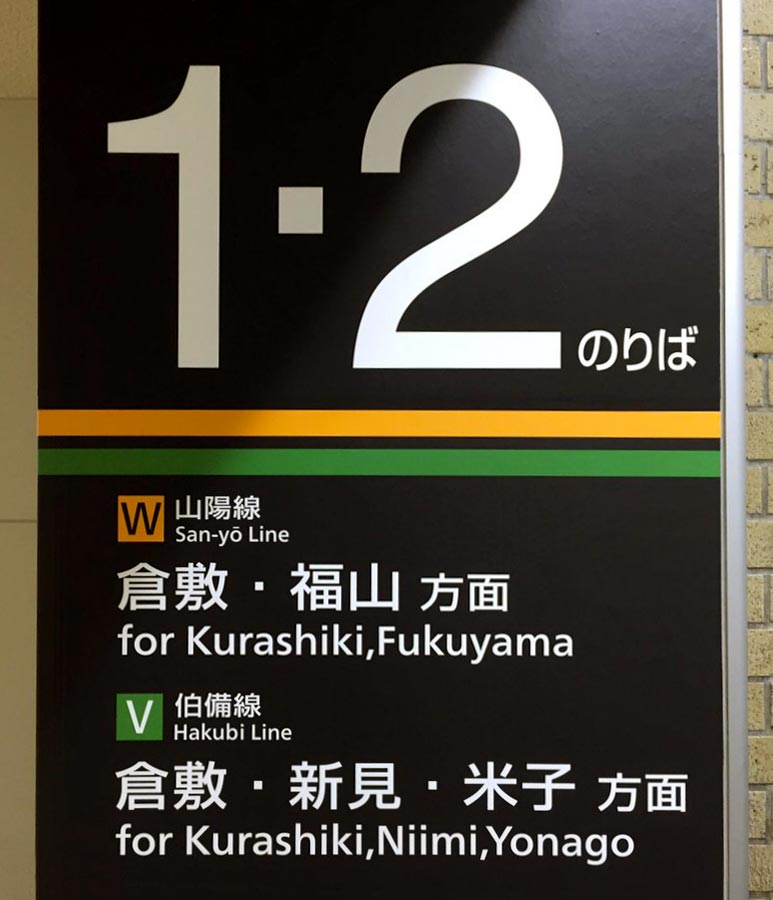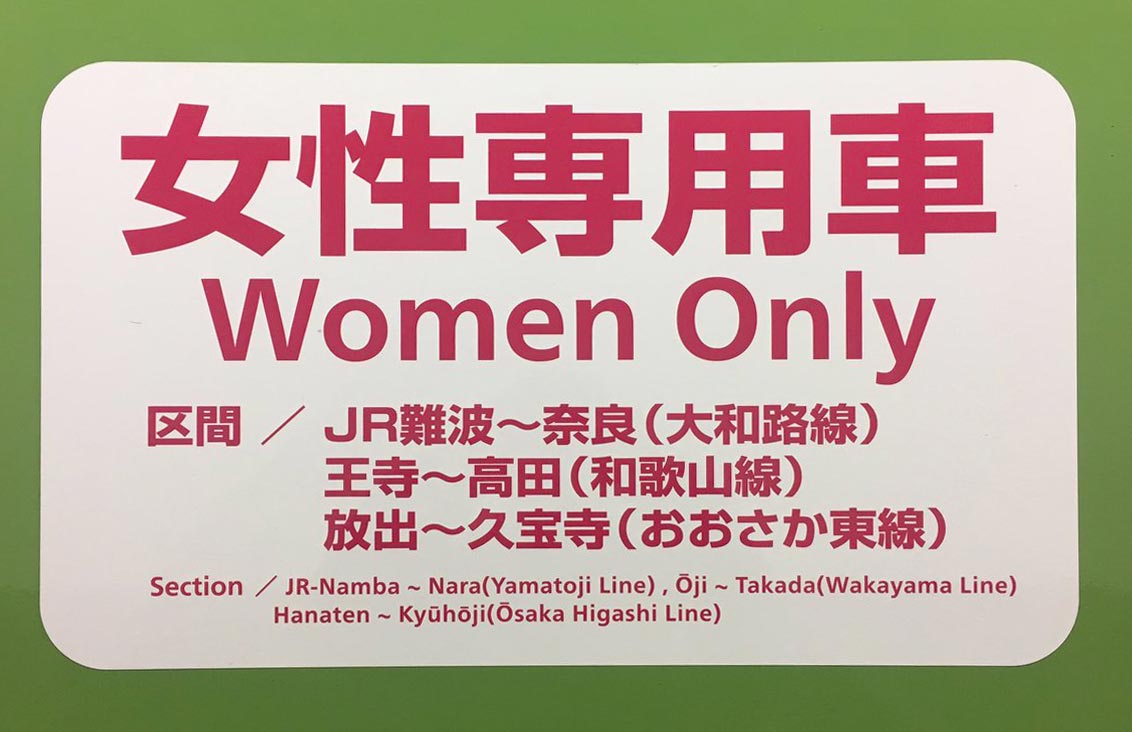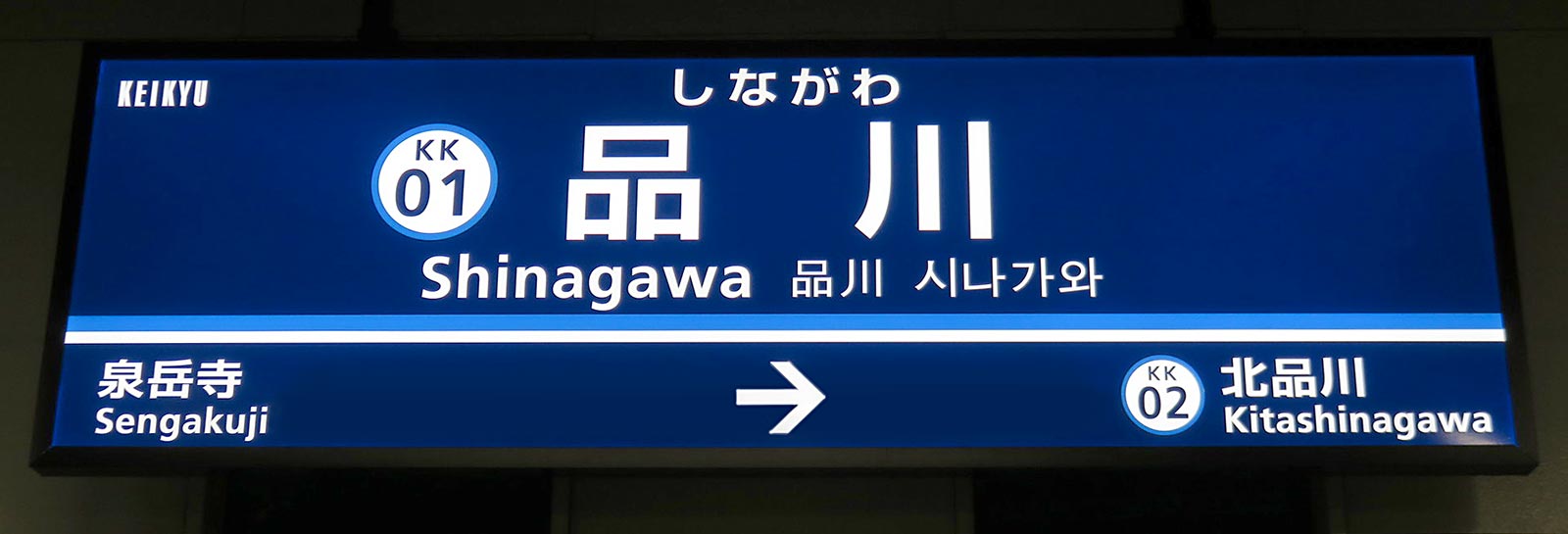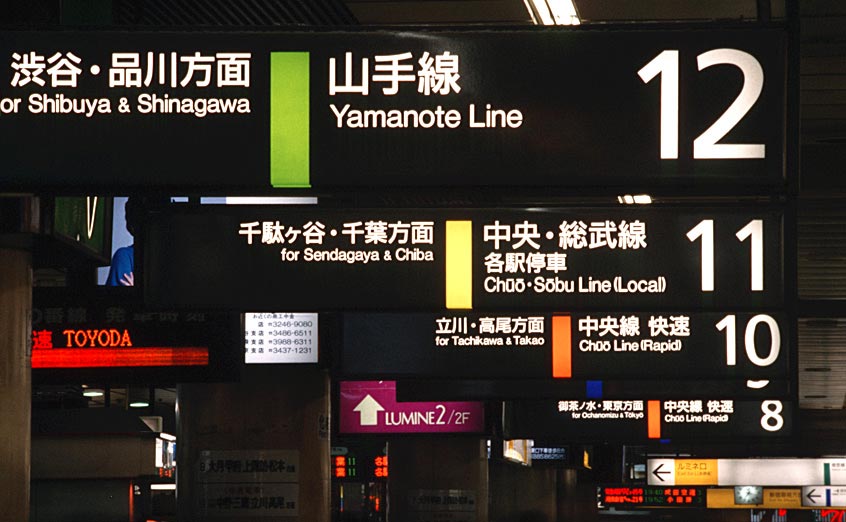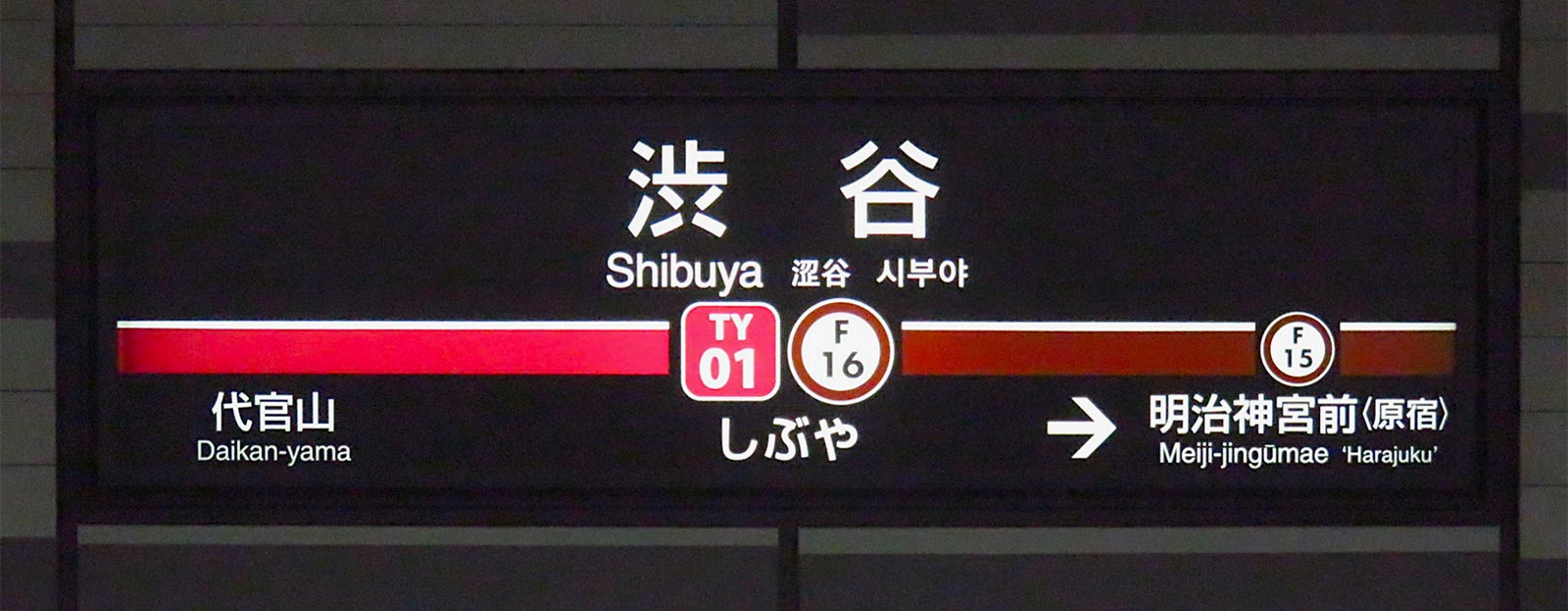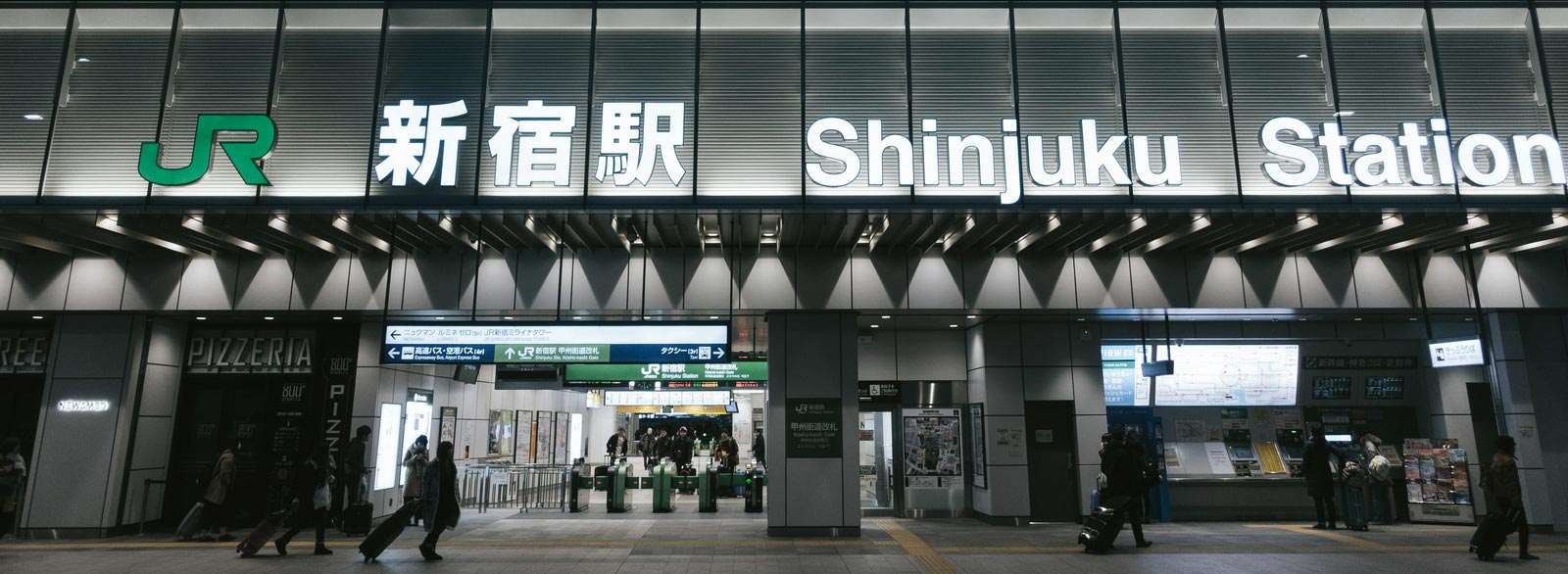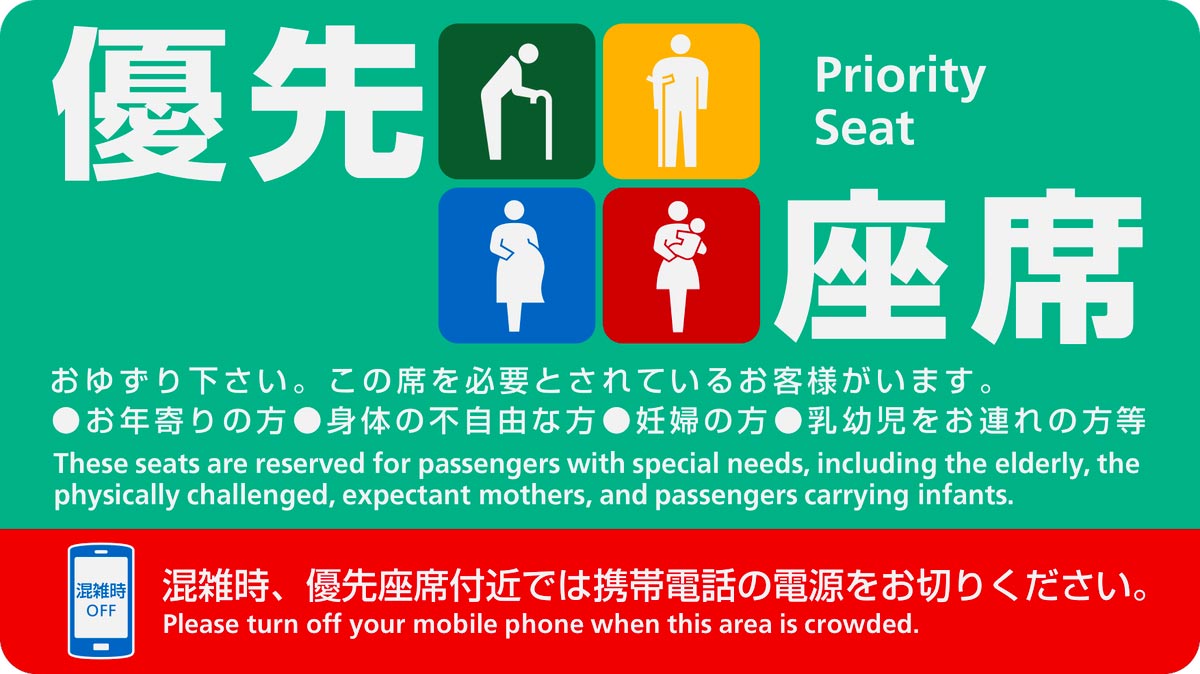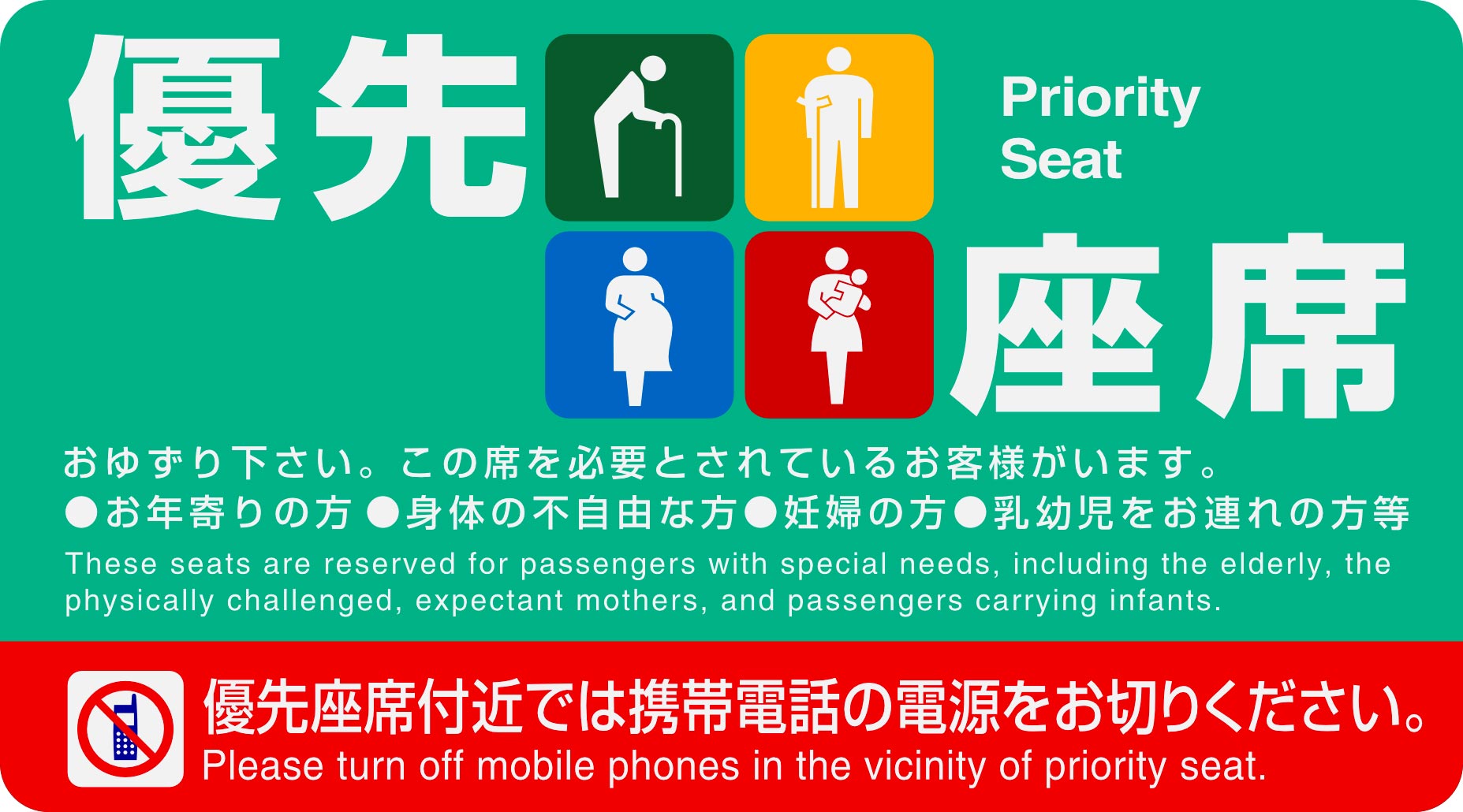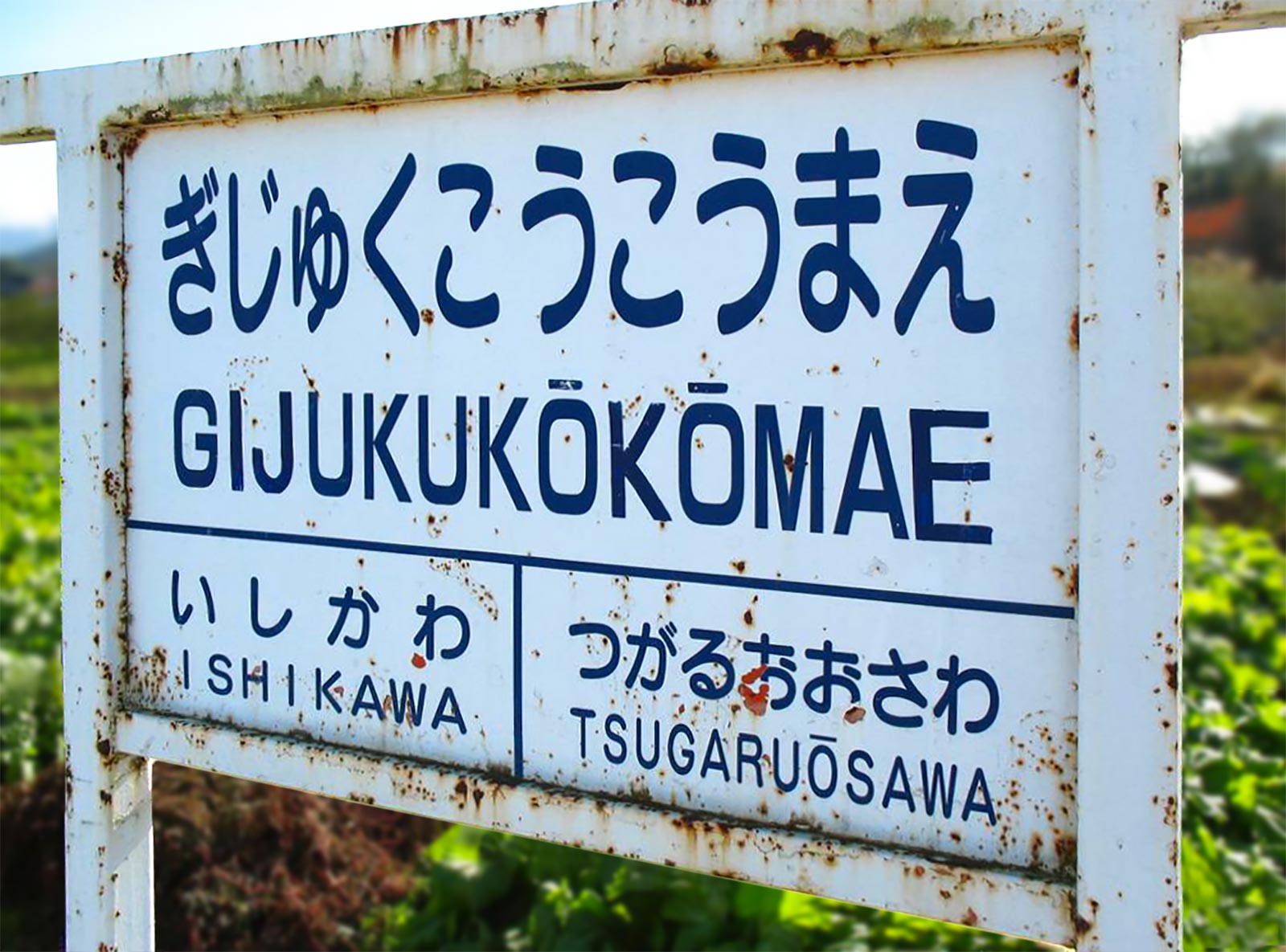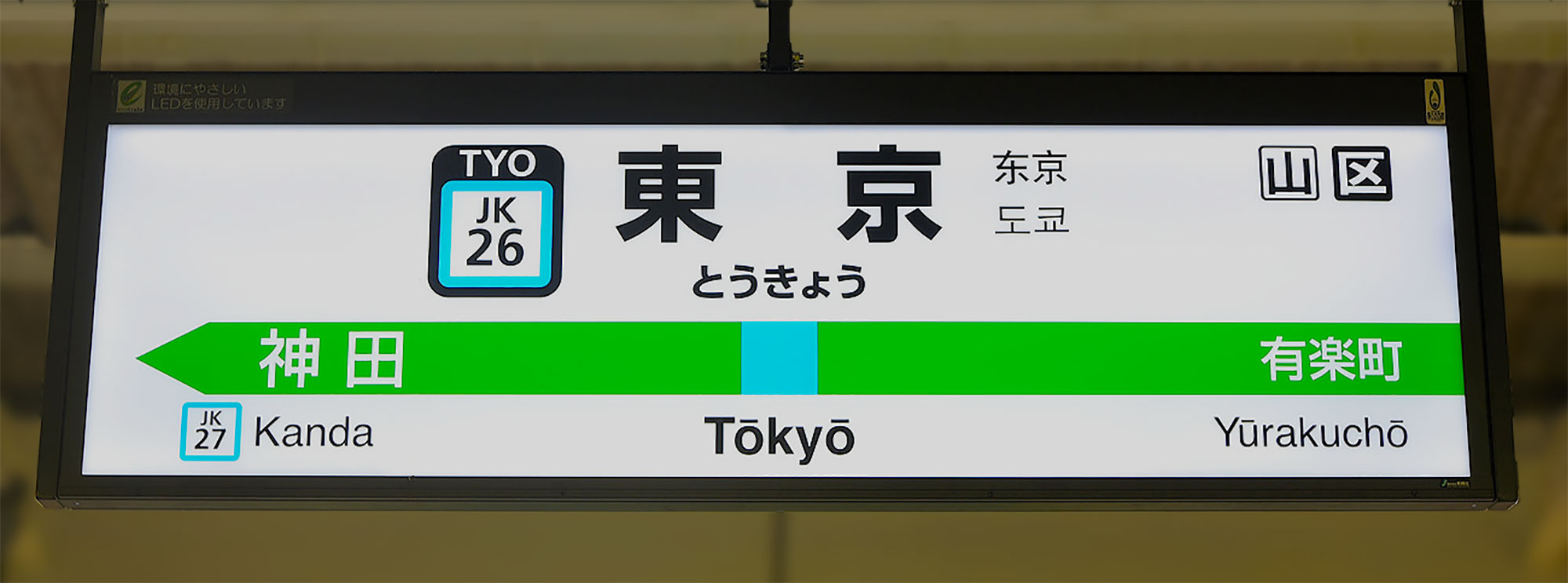
Japan und das Alphabet
Alphabet im japanischen Alltag
Ein Bahnhofsschild in der Präfektur Aomori
Die Japaner haben es eigentlich nicht nötig, das lateinische Alphabet zu verwenden. Aber die westlichen Kulturen übten eine große Faszination auf sie aus und viele fanden die lateinischen Buchstaben ziemlich schick. Die Folgen hiervon sind im japanischen Alltag heutzutage unübersehbar, und sie sind nicht immer erfreulich.
Schon immer aufnahmefähig
Ursprünglich besaßen die Japaner keine eigenständige Schrift. Sie haben es den Chinesen zu verdanken, dass sie überhaupt mit dem Schreiben beginnen konnten. Vermutlich deshalb hatten Japaner auch später nie Hemmungen bei der Verwendung fremder Schriften in ihrer Schreibkultur, so dass das lateinische Alphabet bedenkenlos von ihnen integriert wurde*.
• Portugiesische Missionare kamen Ende des 16. Jahrhunderts nach Japan, um ihre Religion in Japan zu verbreiten. Mit ihnen kam das lateinische Alphabet. Aber das Christentum wurde recht bald von der Regierung verboten und Japan schottete sich für ca. 250 Jahre weitgehend von der Außenwelt ab, was auch für das Alphabet das vorläufige Ende bedeutete. Erst nach der Meiji-Restauration 1868 bekam das Alphabet starken Aufwind und begann die japanische Gesellschaft zu durchdringen.
Helvetica! Helvetica!
Wie gesagt brauchen die Japaner das Alphabet nicht, um ihre Sprache zu schreiben. Man könnte sagen, dass lateinische Buchstaben hauptsächlich fürs Schmücken verwendet werden und weniger dafür, dass jemand sie liest. Die simplen, rationalen Formen der Buchstaben sind es, was die Japaner so fasziniert. Klare, zeitlose und unpersönliche Schriftarten sind besonders bei Designern beliebt. Einmal dürfen Sie raten, welche Schriftart dort am meisten gefragt ist – richtig, die Helvetica.
Helvetica Shinjuku
Bahnhof JR Shinjuku
Wer Japan besucht und kein Japanisch versteht, sucht nach Informationen in lateinischen Buchstaben und findet sie auch überall. Auf den Bahnhofsschildern stehen die Namen des aktuellen Bahnhofs und der – soweit der Bahnhof keine Endstation ist – zwei angrenzenden Stationen meist auch in lateinischen Buchstaben.
Typografie in Japan, Bahnhofsschild Tokyo
Tōkyō Station. Das »ō« (o Makron) sieht man fast ausschließlich in Ortsbezeichnungen. Es zeigt an, dass der Vokal lang, wie Honig, ausgesprochen wird.
Typografie in Japan, Bahnhofsschild Shibuya
Shibuya Station der Tōkyū Tōyoko-Linie. In Japan ist nicht festgelegt, wo genau eigentlich ein Bindestrich gesetzt wird. Er ist genau genommen kein Bindestrich sondern er funktioniert wie ein Trennstrich, der für eine richtige Silbentrennung bei der Aussprache sorgt.
Frutiger Shinjuku
Frutiger in Shinjuku, 1988 ©GK Design Group
Frutiger im Aufwind
Die Schrift Frutiger wurde bereits im Jahre 1988 für das neue Orientierungssystem der JR-Linien im Bahnhof Shinjuku, einem der verkehrsstärksten Bahnhöfe der Welt, eingesetzt – allerdings nur ihre Ziffern für die Nummerierung der Bahnsteiggleise. Der Rest (das lateinische Alphabet) wurde in Helvetica gesetzt. Vielleicht waren den Japanern damals noch die Buchstaben der Frutiger zu fremd aber immerhin; man könnte das als der erste Emanzipationsversuch der japanischen Designer bezeichnen.
Noch eine Weile sollte jedoch die technische und kalte Helvetica in Japan DIE Schrift für lateinische Buchstaben bleiben. Aber die humanistische und warme Frutiger gewinnt zunehmend an Beliebtheit. Die alte Schweizer wird nach und nach durch die modernere Schweizer ersetzt, und das nicht nur bei der JR-Gruppe sondern auch bei anderen Bahngesellschaften, die bislang der Souveränität der Helvetica nie anzweifelten.
Der neue Look bei der Keikyu-Line, einer der zahlreichen japanischen Privatbahnlinien im Ballungsraum Tokio. Seit 2010 ersetzt das Unternehmen schrittweise die ausgediente Helvetica durch Frutiger.
Alt gegen Neu. Altes Handy gegen Smartphone, Helvetica gegen Frutiger ersetzt.
Nur Frauen einsteigen, bitte! Mittlerweile gibt es auch im Westen Japans neue Waggons für Frauen und eine neue Schrift für die Beschilderung. Aber der Setzer dieses Hinweisschildes läuft offensichtlich noch der Zeit hinterher, verwendet wohl unüberlegt »japanische« Satzzeichen für den englischen Satz und setzt natürlich kein Leerzeichen vor der öffnenden Klammer (da das japanische Äquivalent bereits einen Zwischenraum besitzt).
Am Bahnhof Okayama kann man sich noch nicht ganz von der alten Oma trennen und belässt die großen Gleisnummern in Helvetica, während das restliche Alphabet in Frutiger gesetzt ist. Auch diesem Setzer fehlen leider die Grundkenntnisse in Englisch, so dass das arme Komma ohne Leerzeichen danach steht.
Provinz in Japan
Selbst in der Stadt sind die meisten Japaner überhaupt nicht interessiert, was auf den Schildern in lateinischen Buchstaben steht, wie sie aussehen oder gesetzt sind. Denn sie schauen hauptsächlich nur auf die Schriftzeichen, die sie sofort lesen können, klar. Der Rest ist für Ausländer. In der japanischen Provinz sieht man aber sehr selten Ausländer, trotzdem ist alles bestens für sie vorbereitet – das seit Jahren und Jahrzehnten.
Für diejenigen, die nicht verstehen, warum das ein Tabu sein soll, ersetze ich die Schriften durch die allseits bekannten Firmenlogos:
Problem erkannt? Ist das schön? Auch eine Schrift soll man immer so verwenden, wie es der Typedesigner vorbestimmt hat.